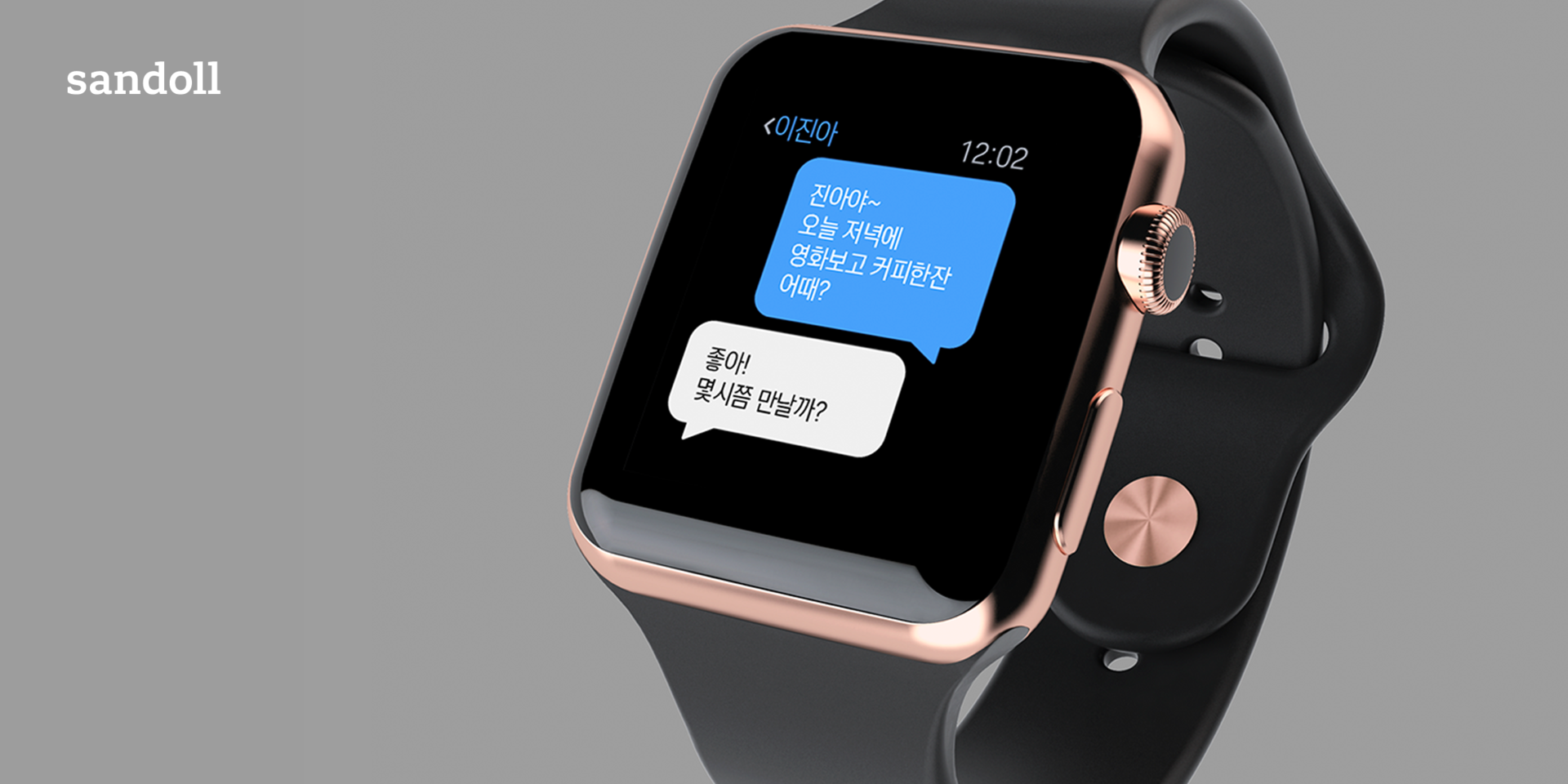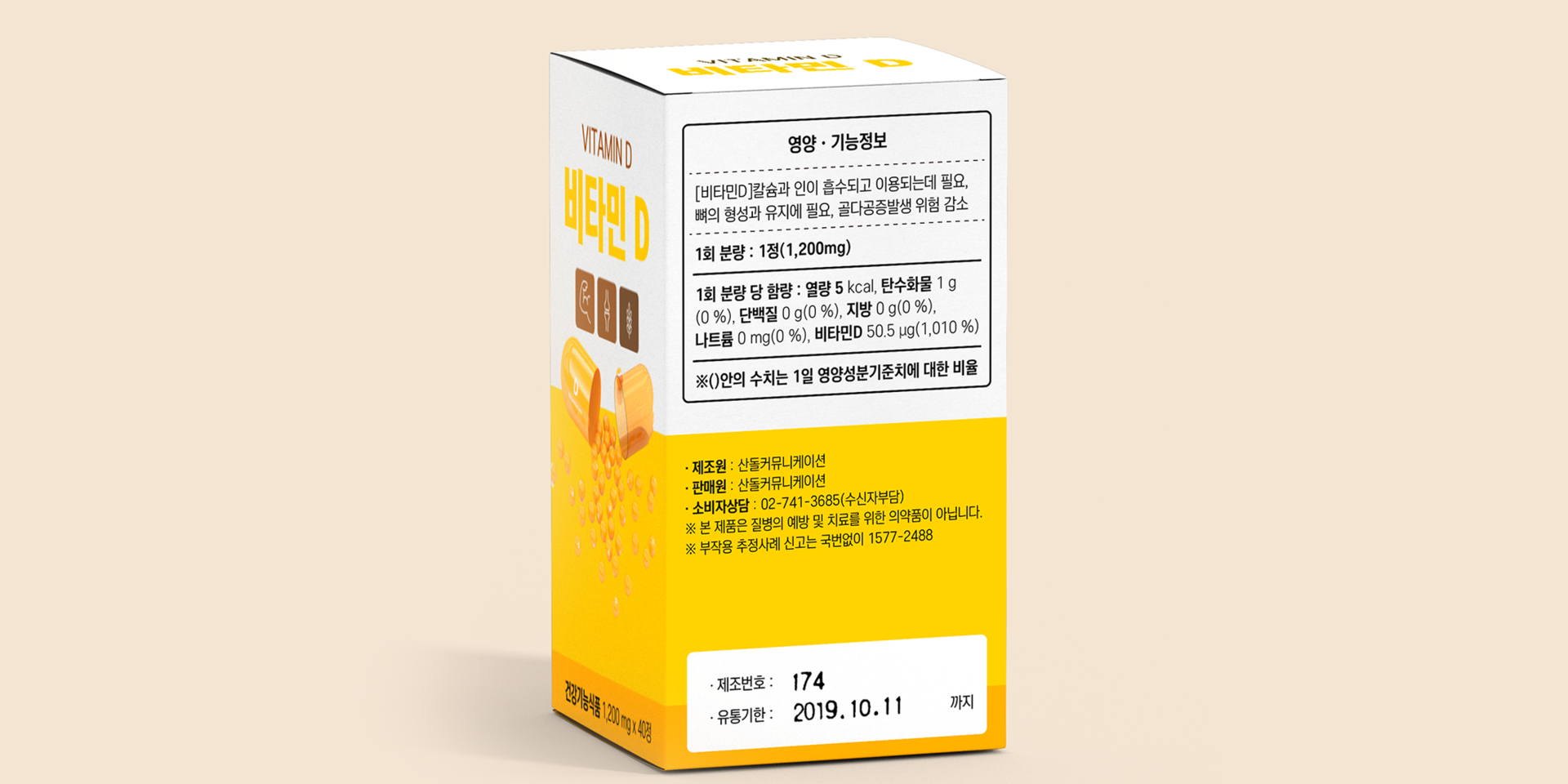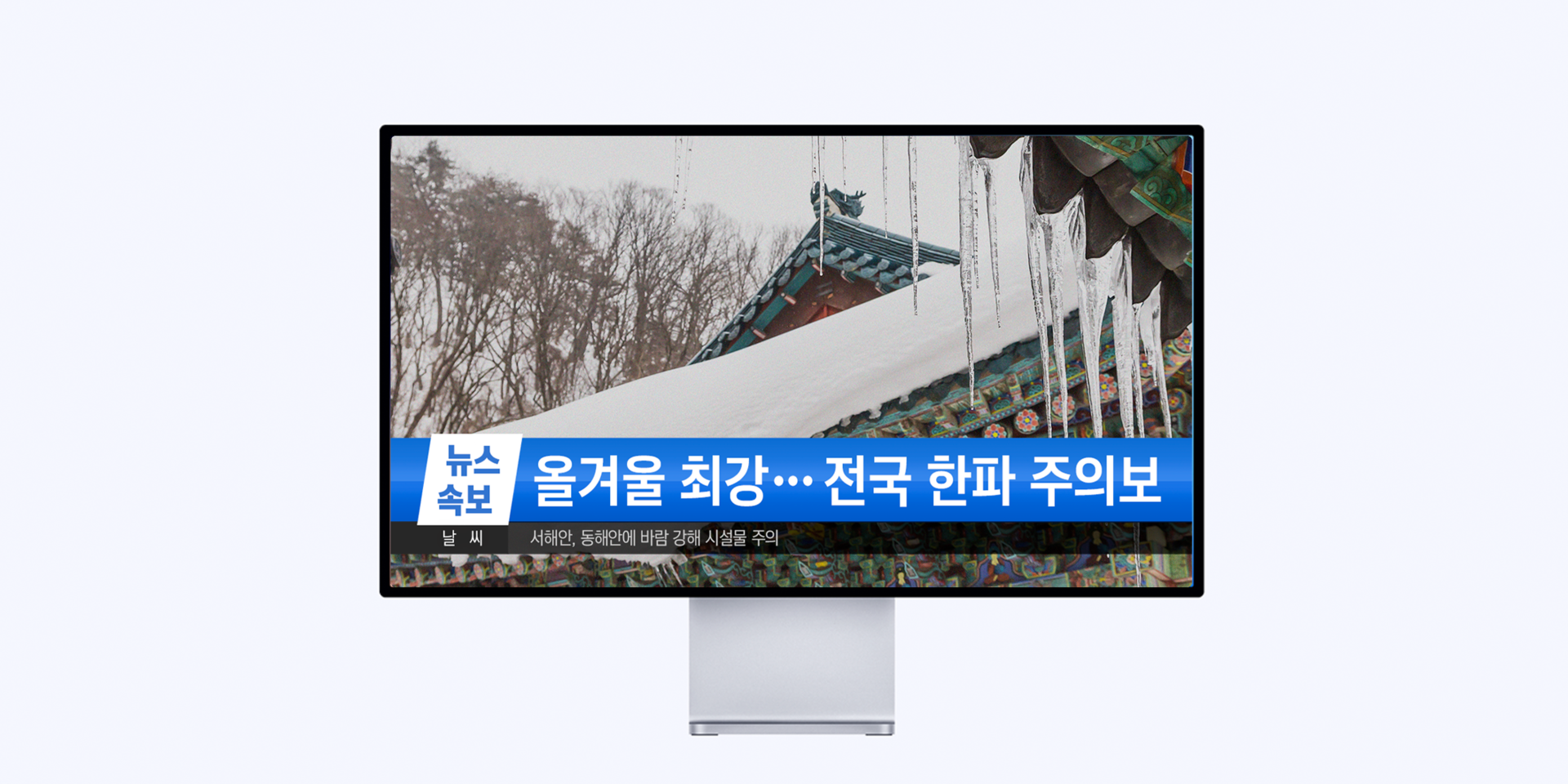
Sandoll 고딕
NeoCond
Neo 시리즈의 6번째 작품으로 국내 최초의 본격 Condensed 서체다.날렵하고, 또렷하고, 치밀한 서체라는 컨셉으로 제작되었으며 글자 공간의 효율적인 활용, 웨이트 간의 굵기를 표현하는 과학적 방법, 디지털 디바이스에 최적화된 높은 가독성이 적용되어 Neo 시리즈의 높은 사용성과 기술력이 집약되었다고 볼 수 있다.